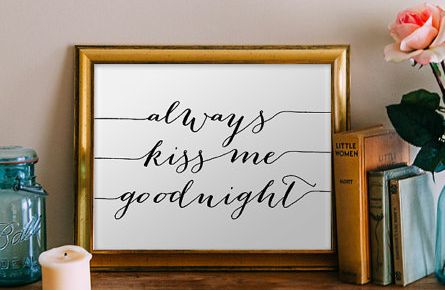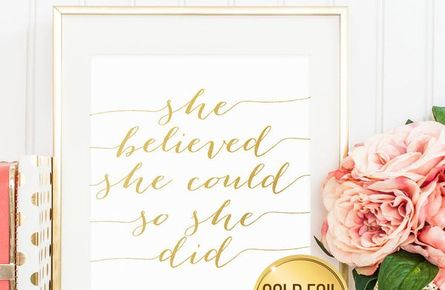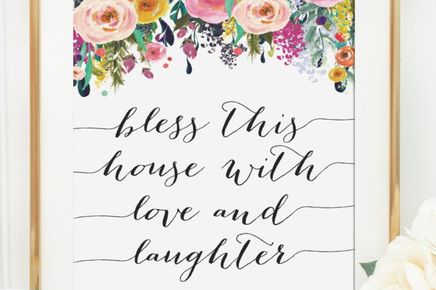
[Шрифт] Bombshell Pro - Рукописный МЕГАпопулярный на Etsy шрифт
Ну очень популярный на Etsy шрифт!
Много красивых глифов.
красота!!!
Возможно, я действительно мало понимаю в типографике, но... этот шрифт ведь очень плохо читаемый.
Если бы вы видели как американцы пишут прописью, то этот шрифт показался бы вам супер-читаемым;)
А это только английский шрифт?
да, русского там нет